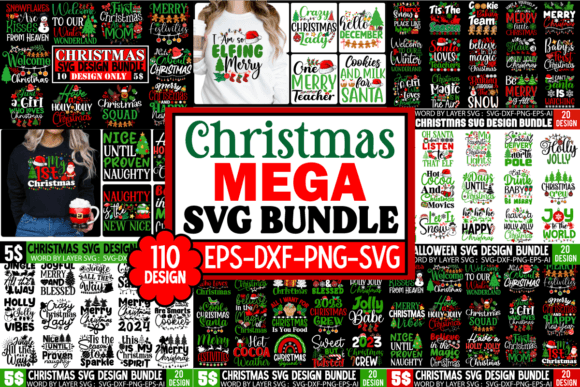
Christmas Mega SVG Bundle
適切なデザイン要素を見つけるのは難しい場合がありますが、Christmas Mega SVG Bundleは作品を即座に引き立てる優れたコレクションを提供します。
精密に作られたChristmas Mega SVG Bundleは、クリーンなベクター、滑らかなタイポグラフィ、そして安心のための商用ライセンスを提供します。